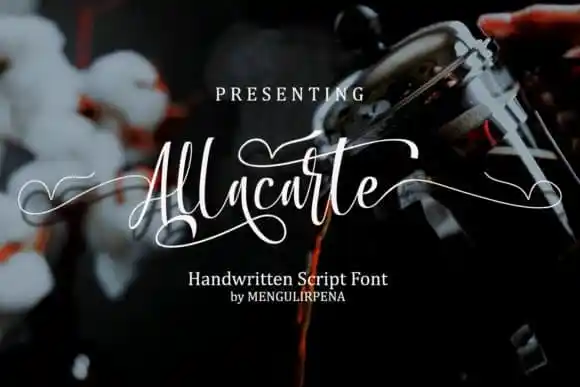
Allacarte Calligraphy Font – Download Grátis
Allacarte Calligraphy Font é uma tipografia de calligrafia suave e encantadora, com cada caractere dançando ao longo do baseline. Este estilo elegante e atraente faz um contraste perfeito entre o sofisticado e o delicado, tornando-o perfeitamente adaptável para os mais diversos tipos de projetos gráficos. A partir da sua utilização em anúncios de casamento até cartões de apreciação, desejos de felicidade ou logomarcas, esta fonte traz uma sensação realista e autêntica que faz falta tanto na web quanto nos documentos impressos. Suas linhas sutis e harmonias perfeitas garantem um touch inovador em qualquer projeto onde seja aplicada, tornando-se uma excelente escolha para aqueles que buscam uma expressão artística em suas criações digitais.